بهترین فونت برای تولید محتوا (معرفی و دانلود 5 فونت کاربردی)
در دنیای امروزی که انواع داده در قالب محتوا در حال بیشتر شدن است، استفاده از فونت مناسب یکی از عوامل کلیدی برای جذب توجه و ارتباط موثر با مخاطبان است. از شبکههای اجتماعی گرفته تا طراحی بنرهای تبلیغاتی، استفاده از بهترین فونت برای تولید محتوا نقش بسیار مهمی در ایجاد هویت بصری و انتقال پیام دارد.
از آنجایی که استفاده از فونت مناسب برای تولید محتوا میتواند تأثیر مستقیمی بر جذب توجه مخاطبان داشته باشد، انتخاب فونتهایی با ویژگیهای خاص و جذاب بسیار حیاتی است. فونتهایی که علاوه بر زیبایی، قابلیت خوانایی و ارتباط با موضوع محتوا را داشته باشند و به عنوان ابزاری قدرتمند پیامها را بهخوبی به مخاطب انتقال دهند.
در این مقاله از وبلاگ فونتچی، به معرفی پنج فونت کاربردی برای تولید محتوا میپردازیم که با داشتن ویژگیهای منحصر به فرد خود، از جمله خوانایی بالا، استحکام در ارتباط با موضوعات مختلف و جذابیت ظاهری، مناسب برای استفاده در تولید محتواهای متنوع در حوزههای مختلف میباشند.
بهترین فونت برای تولید محتوا در شبکههای اجتماعی
انتخاب بهترین فونت برای تولید محتوا در شبکههای اجتماعی از چند جهت اهمیت دارد. اولین و مهمترین مورد، توجه به زیبایی و جذابیت ظاهری فونت است. فونت مناسب رسانههای اجتماعی باید توانایی جلب توجه کاربران را داشته باشد و به وضوح از سایر فونتها متمایز باشد.
همچنین، توجه به خوانایی و قابلیت خواندن فونت در اندازههای مختلف صفحه برای دستگاههای مختلف، از موبایل و تبلت گرفته تا صفحه خوانها و نمایشگرهای بزرگ نیز امری حیاتی است. چرا که بسیاری از کاربران این شبکهها از دستگاههای موبایل استفاده میکنند.
تناسب فونت با موضوع محتوا نیز مسئله مهم بعدی است. فونت خوب برای تولید محتوا که در حوزههای مختلف مد و فشن، فناوری، طراحی، سلامتی و… استفاده میشود، باید با موضوع محتوا همخوانی داشته و به عنوان یک عنصر از هماهنگی و هویت بصری برند عمل کند.
به عنوان مثال، برای محتوای مرتبط با موضوعات فناوری و نوآوری، فونتهایی با طراحی مدرن و پویا مناسب هستند؛ در حالی که برای محتوای مرتبط با موضوعات سلامتی و طب، فونتهایی با طراحی ساده و خوانا ترجیح داده میشود که اکثریت جامعه بهخوبی قادر به خواندن آن باشند.
فونت پیدا با ۹ وزن
فونت پیدا یکی از فونتهای کاربردی و جذاب برای تولید محتوا است که از ویژگیهای بارز آن میتوان به استفاده از خطوط زیبا، نوع زوایا و گردی چشمی و حروف به شیوهای مدرن اشاره کرد. این فونت با طراحی ساده و شیوهای که به آن اعمال شده، قابلیت استفادهی آسان را برای تولید محتواهای مختلف ایجاد میکند.
خوانایی بالا و قابلیت فهم آسان متن از ویژگیهای مهم این فونت است که در قالب ۹ وزن مختلف ارائه شده است. این فونت خوانایی لازم را برای محتواهای متنی چه در بخش عناوین و چه متون طولانی حفظ میکند بهطوری که هرچه از وزنهای بالاتر در سایز بزرگتر استفاده کنید، خود را بیشتر نیز نشان خواهد داد.
همچنین، طراحی شیوا و مدرن فونت پیدا، آن را به فونت مناسب برای محتواهایی که بهدنبال جلب توجه و ایجاد هویت بصری هستند بدل نموده است. وجود حروف و ترکیبات جایگزین نیز دست شما را برای تنوعبخشی به این نکته بازتر میکند.
در مجموع، فونت peyda یک گزینه عالی برای تولید محتواهای متنی و برخی از محتواهای گرافیکی است که به دنبال طراحی مدرن و شیوا هستند. این فونت با استفاده از خطوط زیبا و طراحی ساده، توانایی جلب توجه مخاطبان را دارد و برای ایجاد محتواهایی با ارتباط بصری قوی و خوانایی بالا، مورد استفاده قرار میگیرد.
فونت کلمه با ضخامت بالا
فونت کلمه نسبت به سایر فونتها ضخامت بیشتری داشته و از هین جهت برای ساخت استوری و تامنیل در شبکههای اجتماعی، گزینهی مناسبی است. این فونت با ارائه ۹ وزن مختلف، از سبکهای سبک تا سنگین، امکان انتخاب گزینهای مناسب برای هر نوع محتوا و نیاز را فراهم میکند.
یکی از ویژگیهای برجسته فونت کلمه، وجود زوایا و گردی زیاد در این قلم است که موجب افزایش خوانایی شده است. این ساختار ضخیم در کنار زوایای تند و گاها بسیار نرم، کمک کرده تا متن در استوریها و تامنیلها به خوبی قابل مشاهده و خواندن باشد.
با این حال، در استفاده از وزنهای این فونت باید دقت عمل را داشته باشید؛ چرا که برای برخی محتواها، ممکن است ضخامت بیشتر موجب شلوغی و عدم تعادل در ظاهر محتوا شود. بنابراین، در انتخاب وزن مناسب برای استفاده در محتواهای شبکههای اجتماعی، نیاز به تعادل بین ضخامت و خوانایی متن وجود دارد.
بهطور کلی فونت کلمه با ضخامت بیشتر و امکان استفاده از ۹ وزن مختلف، یک گزینه بسیار مناسب برای استفاده در شبکههای اجتماعی است، خصوصا برای استوری و تامنیل است، که به دیده شدن بیشتر محتوا کمک خواهد کرد.
فونت وریبل دانا با ۱۳ وزن
فونت دانا با داشتن ۱۳ وزن مختلف و پشتیبانی از فونت متغیر (وریبل)، یکی از فونتهای چندمنظوره و وسیع برای تولید محتواست. این فونت با ترکیبی از دوایر، زوایا، خطوط قائم و ساختار ایتالیک، طراحی شده که امکان ایجاد تنوع و تأثیرگذاری بیشتر در ظاهر محتوا را فراهم میکند. علاوه بر این، از چندین سبک نقطهگذاری چسبان و پیوسته در کنار حروف جایگزین، پشتیبانی میکند که آن را به ابزاری قدرتمند برای تنوع و جانبخشی به متن محتوا تبدیل کرده است.
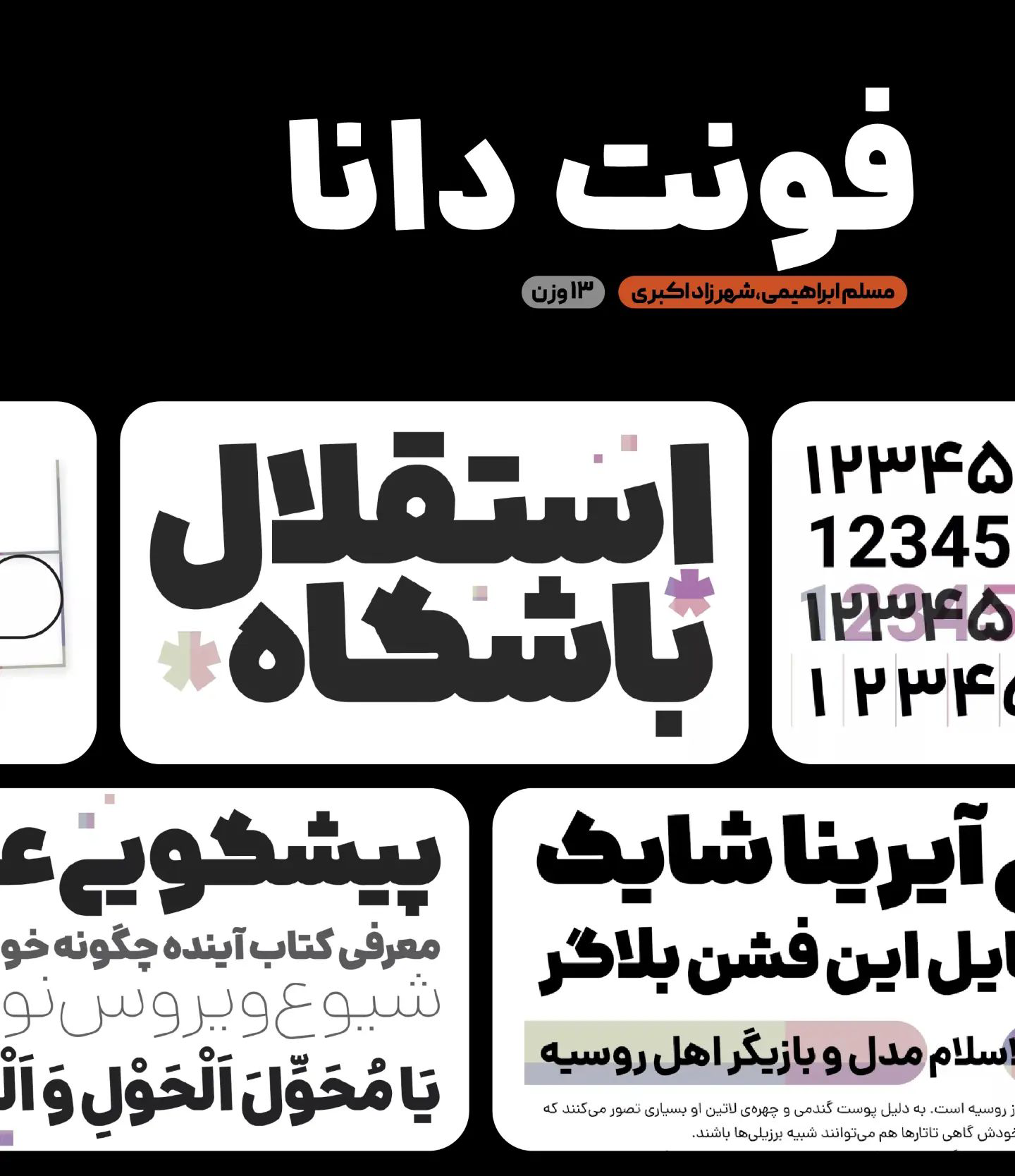
یکی از ویژگیهای بارز فونت دانا، تنوع و انعطاف پذیری آن است. با ارائه ۱۳ وزن مختلف، این فونت امکان انتخاب گزینهای مناسب برای هر نوع محتوا و نیاز را فراهم میکند. این تنوع وزنی به خوانایی فونت کمک کرده تا در انواع نمایشگر بتوانید از وزن مناسب در کنار سایز استاندارد استفاده کنید.
حروف جایگزین در فونت دانا به طراحان اجازه میدهد که، بدون انجام کارهای پیچیده گرافیکی، ظاهر متون را در چند حالت مختلف تایپ کنند. بهویژه در محتواهایی که با هدف تمرکز روی برندینگ باشد که این تنوع در نوع نگارش برخی حروف، باعث جلب توجه بیشتر به دلیل ظاهر متفاوت خواهد بود.
به طور کلی، فونت Dana با ترکیبی از ویژگیهای گوناگون از جمله تنوع، انعطاف پذیری و پشتیبانی از وریبل، جزو بهترین فونت ها برای تولید محتوا محسوب میشود. این فونت با توجه به ویژگیهای منحصر به فرد خود، میتواند به عنوان یک فونت مناسب در رابط کاربری هم مورد استفاده قرار گیرد تا ساختاری یکپارچه به صفحه اجتماعی شما بدهد.
فونت ضخیم یکان بخ
یکی دیگر از فونتهای کاربردی برای تولید محتوا در شبکههای اجتماعی، فونت یکان بخ است که اگر قرار باشد اشارهای به ساختار آن کنیم، به صورت ترکیبی ویژگیهای فونت دانا و کلمه را در خود دارد. این فونت وریبل که از ۸ وزن مختلف پشتیبانی میکند، در عین حال که در وزنهای بالا ساختاری ضخیم دارد، در وزنهای پایین نازک بوده و به مویی بند است.
این فونت با الهام از فونت یکان طراحی شده که پیش از این فونت ایران یکان را نیز با همین ساختار برای دانلود در دسترس قرار دادهایم. ساختار فونت کاملا گرد است و زوایا و چشمیها حالتی رسمی دارند؛ اما در عین حال سعی میکنند تا حدودی خود را نرم و دوستانه جلوه دهند.
این فونت برای عناوین پستها در شبکههای اجتماعی به خوبی میتواند نگاه مخاطب را به خود معطوف کند. خصوصا زمانی که از حروف و ترکیبات جایگزین آن برای تنوعبخشی به متن خود استفاده کنید. وزنهای سنگین این فونت ضخامت مناسب را برای دزدیدن نگاه مخاطب در اختیارتان قرار میدهند.
به طور کلی فونت YekanBakh میتواند یک انتخاب هوشمندانه برای فونت عناوین در تولید محتوا باشد که از وزنهای معمولیتر میتوانید برای فونت متون خود نیز استفاده کنید. همچنین این فونت از سبک نقطهگذاری پیوسته پشتیبانی میکند که در نسخه وریبل میتوانید از چند حالت مختلف نقطهگذاری هم استفاده کنید.
فونت کوک با ۶ وزن
اگر به دنبال فونت جدید برای تولید محتوا هستید، فونت کوک میتواند جذابیت ظاهری فوقالعادهای در متن شما ایجاد کند. چرا که از تنوع بالایی برای حروف جایگزین برخوردار بوده و سبک زوایا، چشمیها، گردی و دندانهها به صورت ترکیبی از دایره و لوزی است.
به منظور نمایشیتر کردن این فونت، حروف و ترکیبات جایگزین متعددی برای آن درنظر گرفته شده است که در کنار سبک نقطهگذاری پیوسته و جدا میتواند به تنوع دادن کلمات نیز کمک کند.
این فونت دارای ۶ وزن مختلف است که در تمامی وزنها طراحی تمامی حروف با کنتراست استانداردی رعایت شده تا در وزنهای کم و با سایز کوچک نیز همان ویژگیهای ظاهری بتوانند خود را به خوبی نشان دهند.
با اینکه فونت Kook هنوز از نسخه وریبل پشتیبانی نمیکند، اما انتظار میرود که در نسخههای آتی نسخه وریبل نیز به آن افزوده شود تا امکان استفاده حرفهایتر از این فونت برای استفاده در سایت نیز به سادگی همان نسخه نرمافزاری در دسترس باشد.
جمعبندی نهایی
در نهایت، فونتها نقش بسیار مهمی در تولید محتوا دارند، به ویژه در شبکههای اجتماعی که به لطف هوشمندتر شدن الگوریتمها، رقابت برای جلب توجه رنگ و بوی تازهای به خود گرفته است. انتخاب فونت مناسب، علاوه بر جلب توجه، باید خوانایی بالا، توانایی انطباق با موضوع محتوا و ایجاد هویت بصری منحصر به فرد را داشته باشد.
از میان فونتهایی که در این مقاله بررسی کردیم، هرکدام ویژگیها و ویژهنماییهای خود را دارند. فونت پیدا با طراحی مدرن و خوانایی بالا، مناسب محتواهای متنی و گرافیکی است. فونت کلمه با ضخامت بیشتر و امکان استفاده از ۹ وزن مختلف، میتواند برای محتواهای استوری و تامنیل مناسب باشد.
فونت دانا با پشتیبانی از ساختار وریبل و ۱۳ وزن مختلف، گزینهای چندمنظوره برای تولید محتواهای مختلف است. یکان بخ نیز با طراحی ضخیم و وزن ششگانه خود که ترکیبی از ویژگیهای دانا و کلمه را دارد، میتواند برای ایجاد محتوای قوی و جذاب استفاده میشود. در نهایت، فونت کوک هم با ترکیبی از ساختار گرد و مربعی، گزینهای جذاب برای تولید محتوا در شبکههای اجتماعی است.
با توجه به نیازها و هدف، دانلود فونت مناسب برای تولید محتوا بسیار اهمیت دارد. باید به دقت و با توجه به موضوع و هویت بصری محتوا، فونت را انتخاب کرد تا بهترین نتیجه را از انتقال پیام به مخاطب گرفت. به نظر شما چه فونتهای دیگری برای تولید محتوا مناسب هستند؟